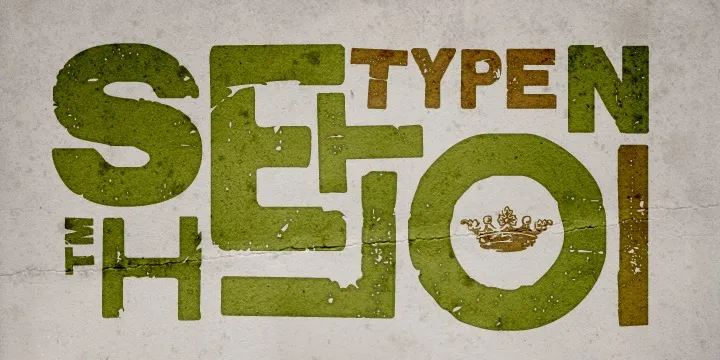
A Shelton Font é uma tipografia com um aspecto frágil e impressa, criando uma sensação de tipo de madeira. As letras parecem ser de diferentes alfabetos para dar um toque de madeira na sua aparência. Cada letra tem um caracter alternativo que adiciona ainda mais diversidade e personalização ao seu projeto. Esta fonte é perfeita para designers que desejam adicionar um toque único e vintage a seus trabalhos, especialmente em projetos decorativos ou artísticos. Se você está procurando por uma fonte com este aspecto reconfortante e sofisticado, então esta é certamente sua opção. A Shelton Font de Hamilton traz uma sensação elegante para qualquer projeto que você estiver criando.